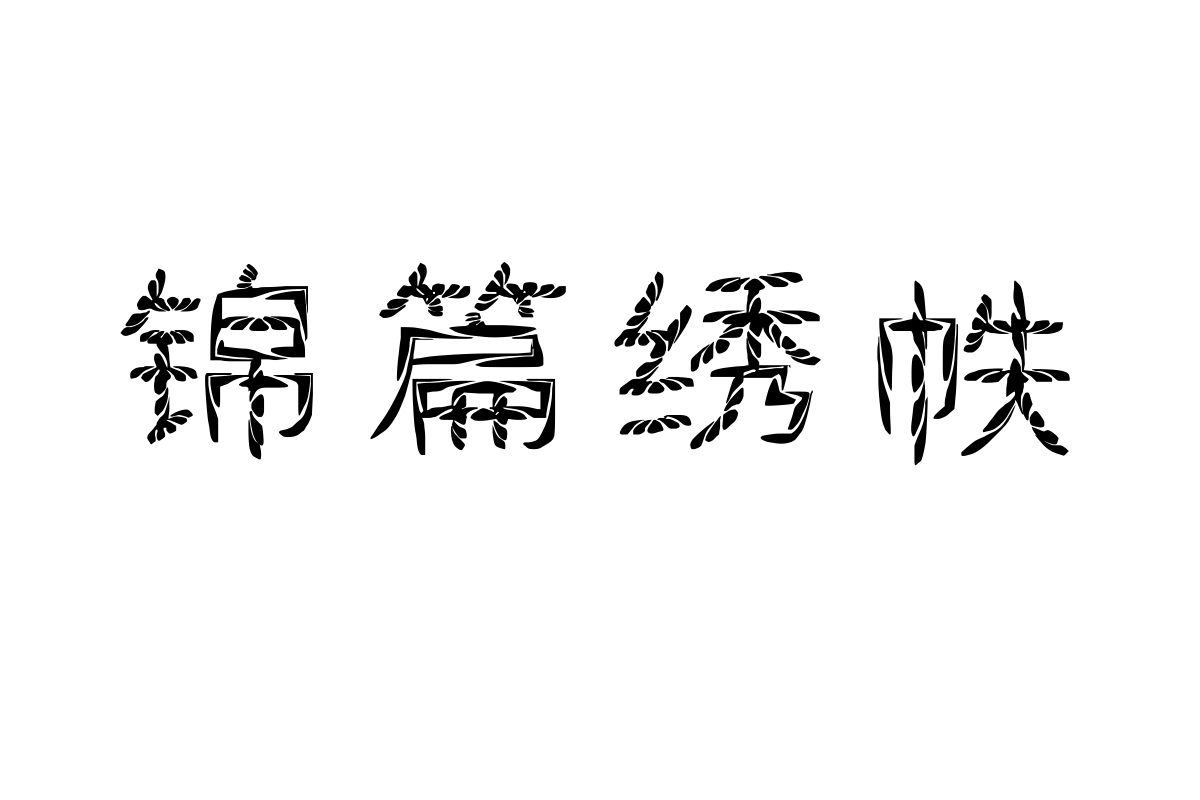
汉标花灯体是一款专为中国春节和元宵节设计的字体。这款字体以其独特的设计和艺术感而闻名,适合用于节日装饰、广告宣传、海报设计等多种场景。
汉标花灯体的字体特点如下:
1. 字形独特:汉标花灯体的字形设计独特,线条流畅,富有中国传统美感。这种独特的字形使得字体在视觉上更具吸引力,能够引起人们的兴趣和关注。
2. 艺术感强:汉标花灯体的字体具有强烈的艺术感,线条粗细变化丰富,给人一种优雅、高贵的感觉。这种艺术感使得字体更加适合用于需要强调传统文化的场合。
3. 易于辨识:汉标花灯体的字体结构简单明了,易于辨识。这使得它在各种应用场景中都能够快速被识别出来,提高了使用效果。
4. 适用性强:汉标花灯体的字体适用于多种场合,如节日装饰、广告宣传、海报设计等。它的适用范围广泛,能够满足不同用户的需求。
总之,汉标花灯体是一款具有独特设计和艺术感的字体,非常适合用于中国春节和元宵节等传统节日的宣传和装饰。